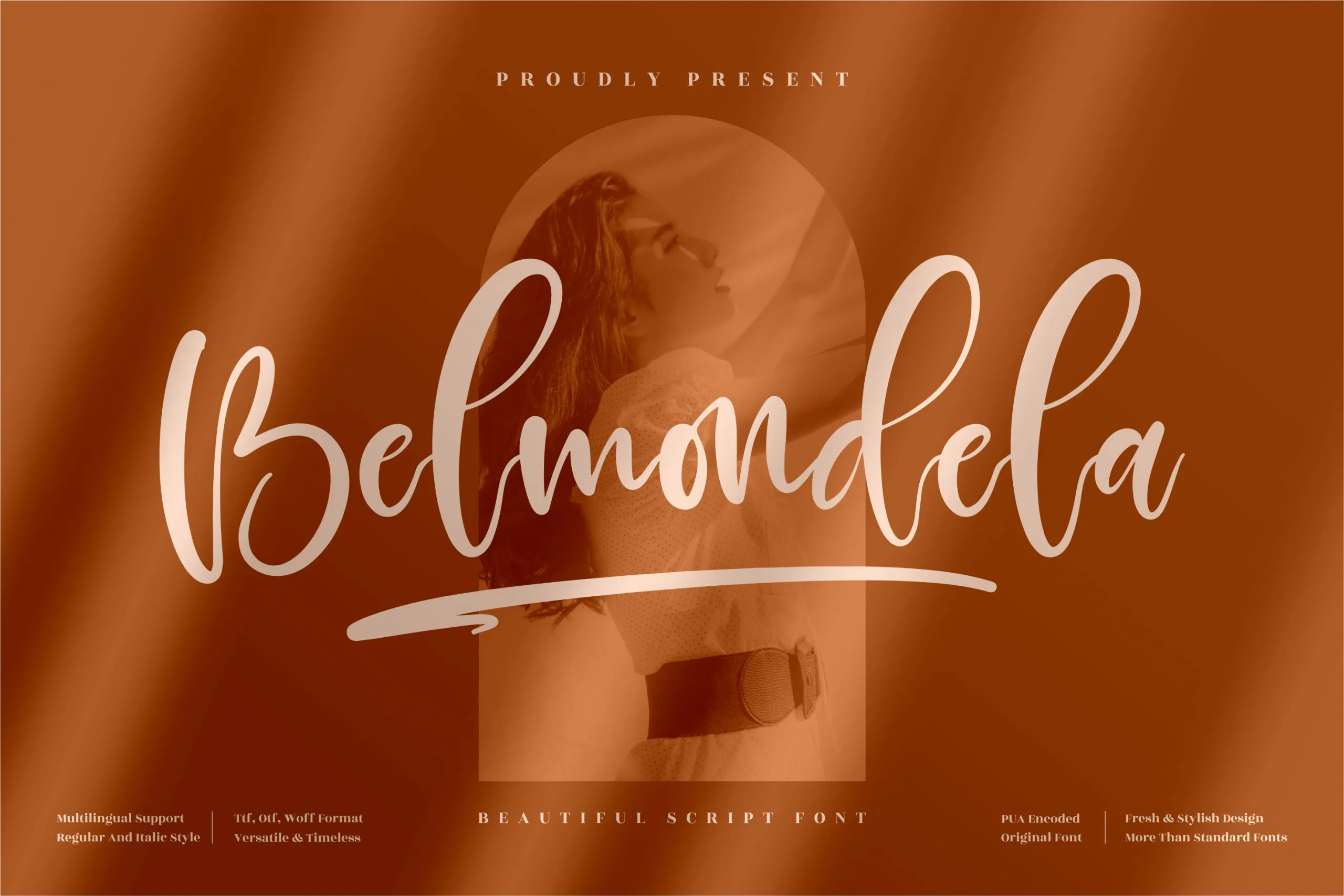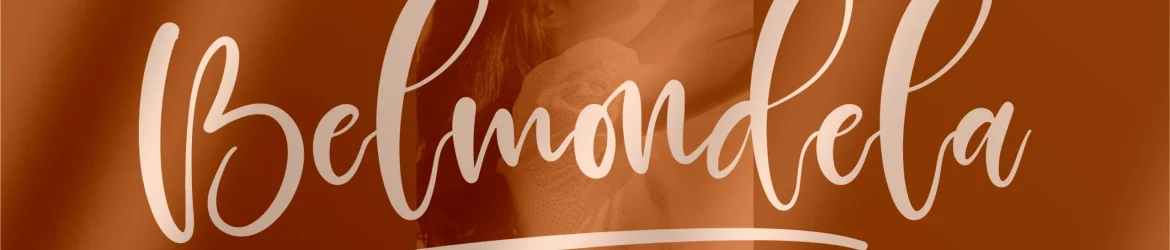
Belmondela Font – Download Grátis
Belmondela Font é uma linda tipografia escrita à mão perfeita para projetos diversos, especialmente aqueles que valorizam a elegância do texto em forma de letra. Seja para criar um logotipo sofisticado ou decorar seus produtos com o charme da escrita à mão. Esta fonte ideal é ideal para designs de mobiliário, embalagens de produto, capas de livros e até mesmo para personalizar suas peças de roupas. Suave e autêntica, Belmondela atende a qualquer necessidade que precise de um toque de elegância no seu projeto visual. Seja para criar uma cartinha especial ou até mesmo uma camisa de algodão doce com um design incrível, Belmondela é sua fonte preferida.